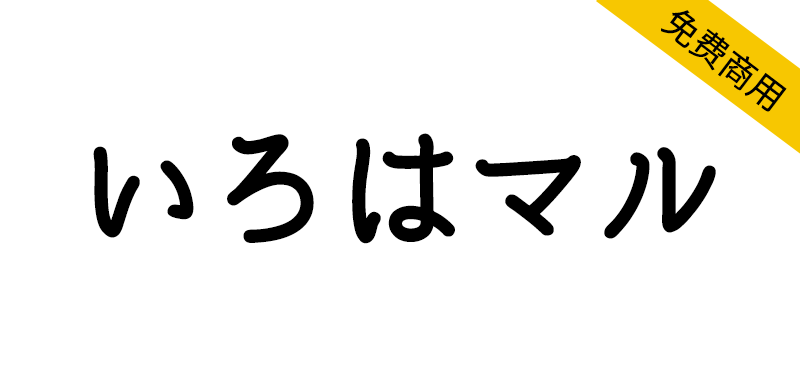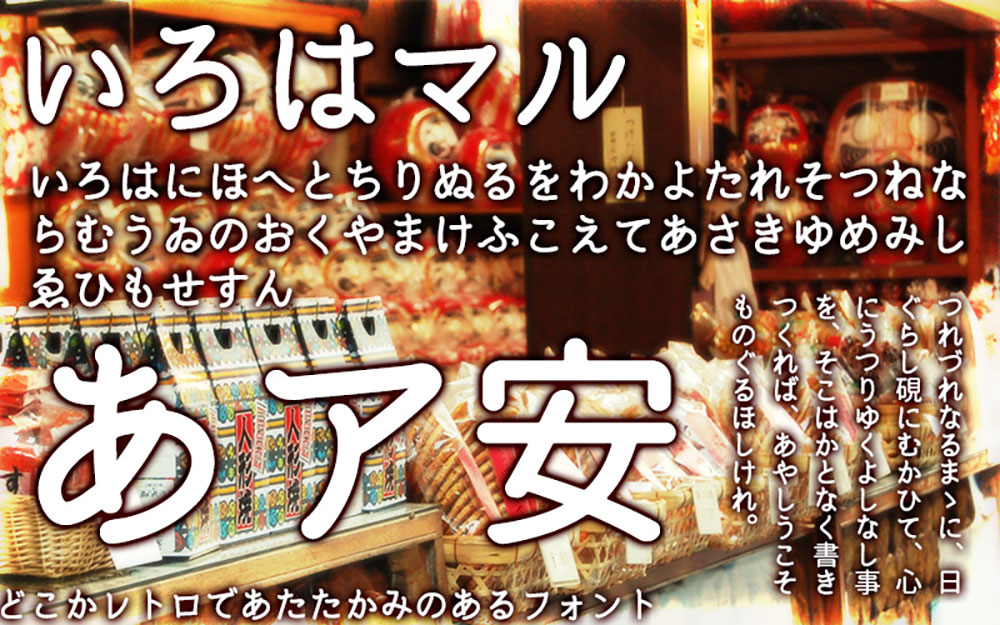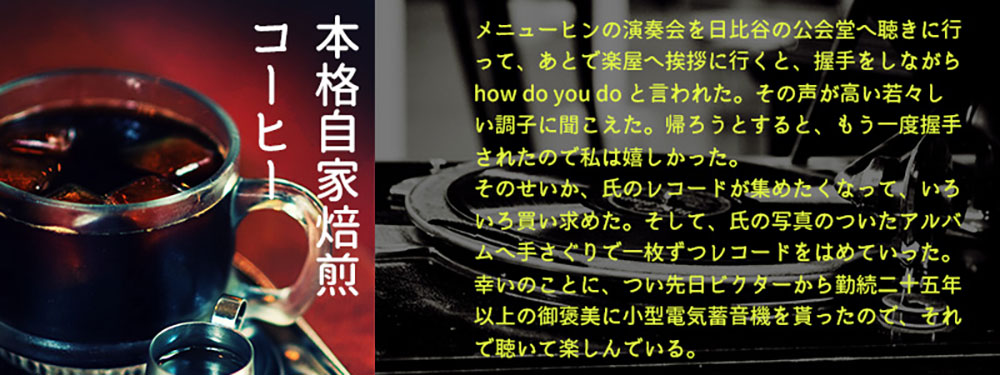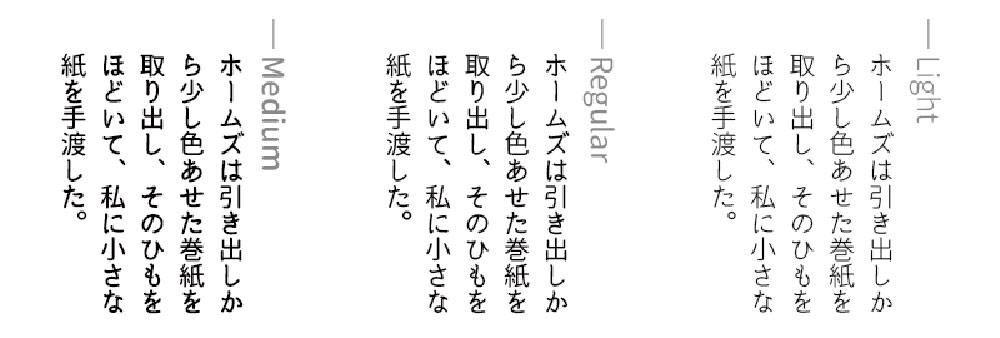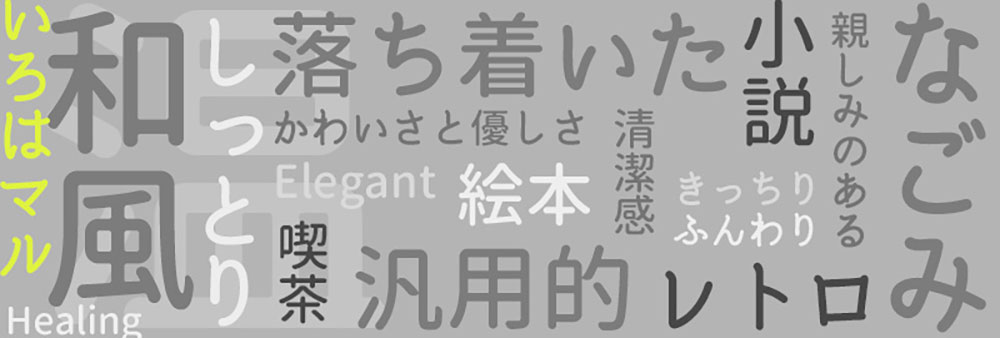
いろはマル(irohamaru)是一款基于源柔黑体的衍生字体,并具有原始的平假名,片假名和一些其他符号。它是一种易于使用的字体,具有圆形哥特式的感觉,但又有点复古的感觉。如果你仔细观察,你会发现平假名和片假名柔软而宽松,给人一种味道和温暖的感觉。
源ノ角ゴシックの派生フォントである『源柔ゴシック(自家製フォント工房/MM様)』の漢字を用い、ひらがな・カタカナ・その他一部記号をオリジナルにした改変フォントです。丸ゴシックながらどことなくレトロ感の漂う、使い勝手の良いフォントです。よく見るとひらがな・カタカナは、ふにゃっとしていたり、ガタつきがあったり、味とあたたかみとして効果になっているんじゃないかと思います。